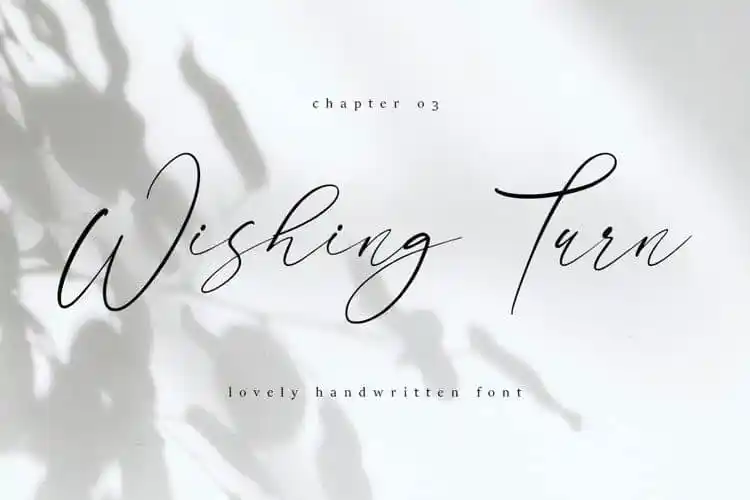
Wishing Turn Script Font – Download Grátis
A Wishing Turn Script Font é uma fonte de estilo script com formas elegantes em cada caracter, criada pelo designer Dav Studio em 99designs. Este tipo de fonte é feito à mão e oferece variações que o tornam perfeito para combinação, especialmente quando você está criando materiais como cartões de negócios, cartas de boas-vindas, conteúdo do YouTube ou qualquer outro projeto onde um toque elegante seja desejado. Com uma aparência tão sofisticada e delicada, a Wishing Turn Script Font se torna perfeita para aqueles que buscam personalizar seus projetos com um toque único e artístico. Seja você um designer gráfico ou simplesmente alguém que adora criar algo especial com suas próprias mãos, esta fonte pode ser sua nova parceira de criação.